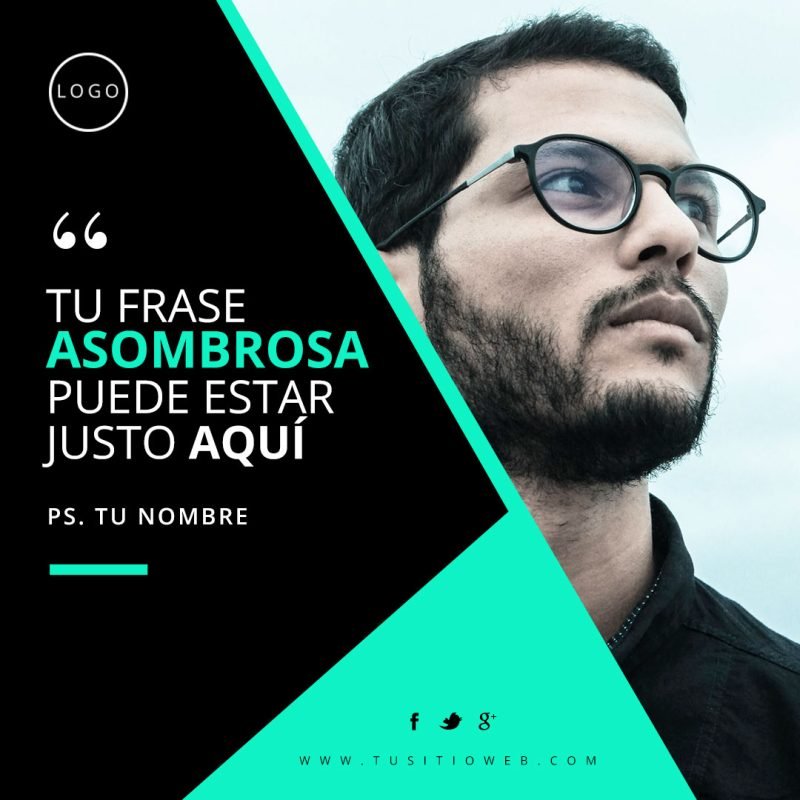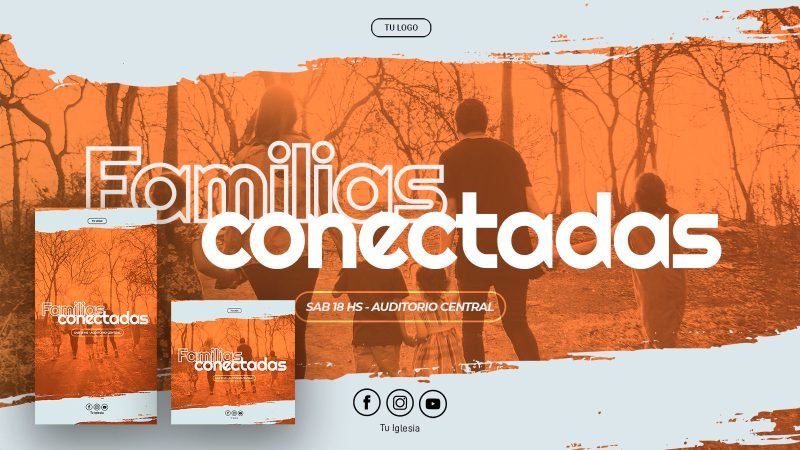
Sabemos que uno de los principales desafíos para quienes estan aprendiendo a diseñar son el uso de las fuentes. ¿Cuál elegir entre tantas?, ¿Cuál se adapta mas a nuestras necesidades?.
El primer consejo que quiero darte es que aprendas a usar las fuentes mas elementales, gratuitas y mas usadas por su versatilidad y facilidad de manejar. Te dejo un listado de fuentes en el que te puedes enfocar si estas aprendiendo a diseñar.
- Montserrat: Esta fuente es una de las más populares en la actualidad. Es una fuente sans-serif que se caracteriza por su legibilidad y simplicidad. Además, es gratuita y está disponible en Google Fonts 1.
- Open Sans: Esta fuente también es muy popular y se utiliza en muchos diseños modernos. Es una fuente sans-serif que se caracteriza por su claridad y legibilidad. También es gratuita y está disponible en Google Fonts 1.
- Roboto: Esta fuente fue diseñada por Google y se utiliza en muchos diseños modernos. Es una fuente sans-serif que se caracteriza por su claridad y legibilidad. También es gratuita y está disponible en Google Fonts 1.
- Lato: Esta fuente es muy popular en la actualidad y se utiliza en muchos diseños modernos. Es una fuente sans-serif que se caracteriza por su claridad y legibilidad. También es gratuita y está disponible en Google Fonts 1.
- Raleway: Esta fuente es muy popular en la actualidad y se utiliza en muchos diseños modernos. Es una fuente sans-serif que se caracteriza por su claridad y legibilidad. También es gratuita y está disponible en Google Fonts 1.
- Gutenberg: Esta fuente es una de las más utilizadas para diseños cristianos debido a su estilo clásico y elegante 2.
- Nexa Rust Slab Black Shadow: Esta fuente es otra opción popular para diseños cristianos debido a su estilo elegante y sofisticado 2.
Espero que esta lista te sea útil para tus proyectos de diseños cristianos.
Como último tip y consejo de oro es «menos es mas». No te compliques buscando fuentes difíciles de implementar.